InDesign/Illustratorの[プロポーショナルメトリクス]は、フォントが持っている詰め組み用の字幅情報に基づいて文字を詰める機能です。
フィーチャー・タグは横組み用ならpaltで「Proportional Alternate Widths」を短縮したものです。わたしはpaltを「ぴーあると」と読みますが、英語っぽく「ぴーおると」と読む人もいます。「ぱると」も聞いたことがあります。どれでもOKです。
縦組み用プロポーショナルメトリクスのフィーチャー・タグはvpal(Proportional Alternate Vertical Metrics)で、わたしは何のひねりもなく「ぶいぴーえーえる」と言っています。
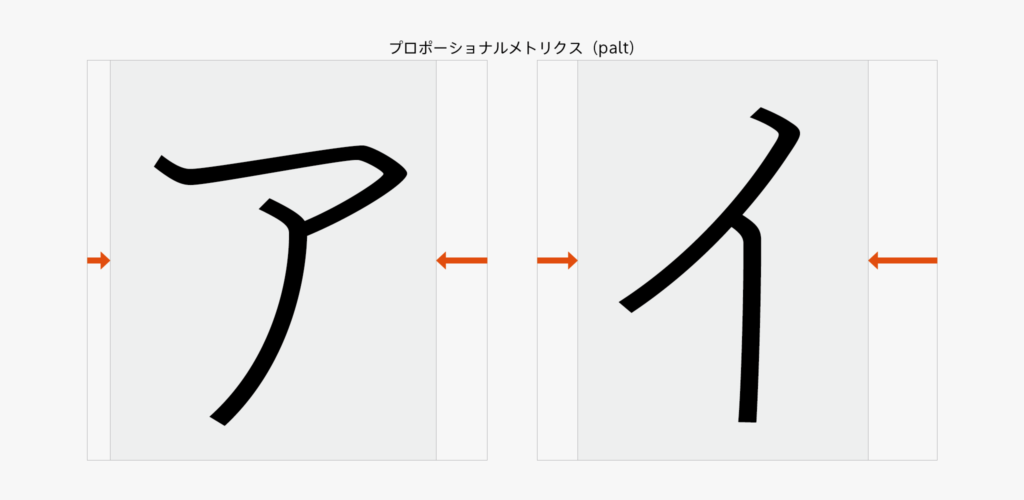
プロポーショナルメトリクスによる文字詰めは、正方形の枠内にデザインされている仮名などのサイドベアリングを調整して、擬似的に欧文のようなプロポーショナルを実現するイメージです。横組みなら、左と右のサイドベアリングをそれぞれ独立に調整します。その値は、フォントメーカーがあらかじめ設定し、フォント内に格納しておいたものです。